书法字体作品中大小字体的规律如何掌握?书圣王羲之在《题卫夫人〈笔阵图〉后》中说:“若平直相似,状如算子,上下方整,前后齐平,便不是书,但得点画耳。昔宋翼(钟繇弟子)常作此书,繇乃叱之,遂三年不敢见繇,即潜心改迹。”
首先:从字体的笔画入手,清楚字的体积大小。
通常字的体积大小是从字体大小来看,古人的书法家字体作品字体的大小间距都非常和谐,是有他的写字规律的。笔画的多少要看字的大小,小的字体要写的大一些。其次笔画多的字写的时候不能很拘谨,如果过于拘谨就没有了字体的形态。下面我找一些古人所写的一些字体作品中给你指出寻找图片上的字体。
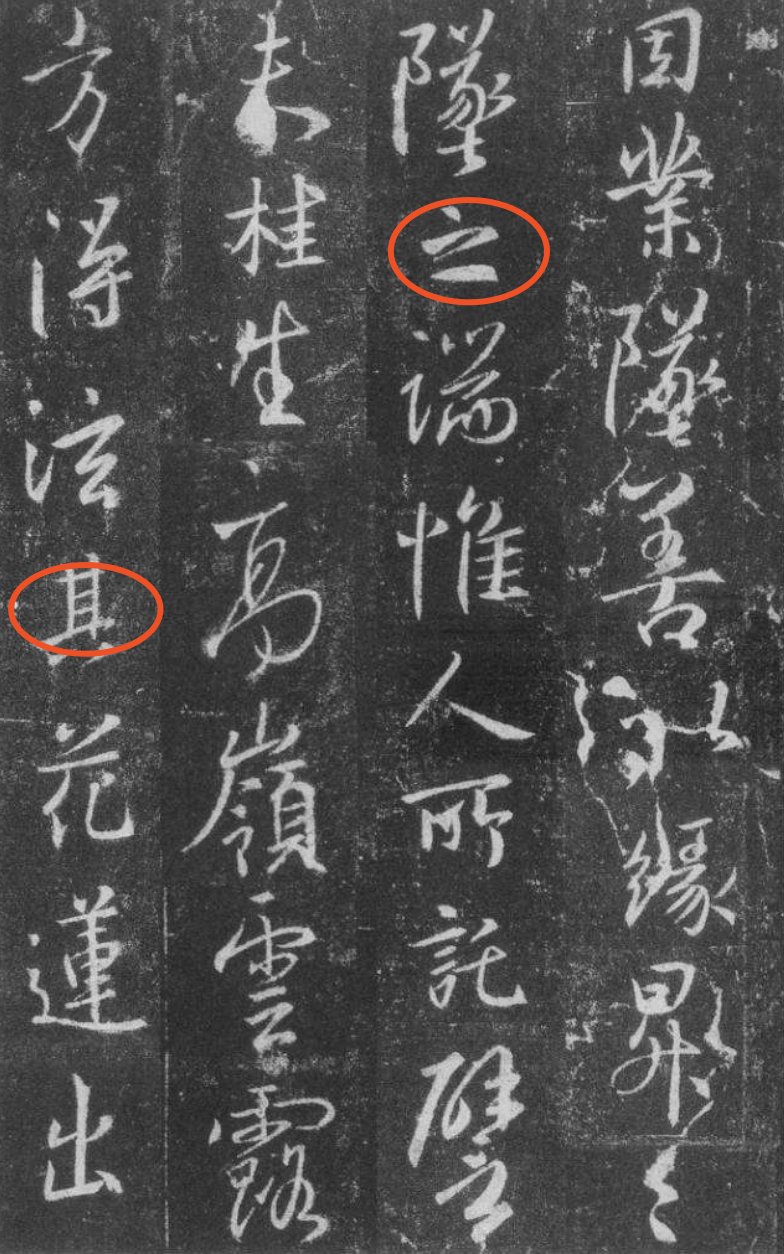
---来源:王羲之碑文
再者:要以字形的美观度来看如果定义字体的大小
以字形的美观程度来确定字体的大小和上面我提到的一样,总的来说就是字体的美观程度高的字体会写的大一些,反之从字形的美观度底的字体你就要写的小一些。一样我也找来古人的字体,从规律中确实有出现图片识别字体。
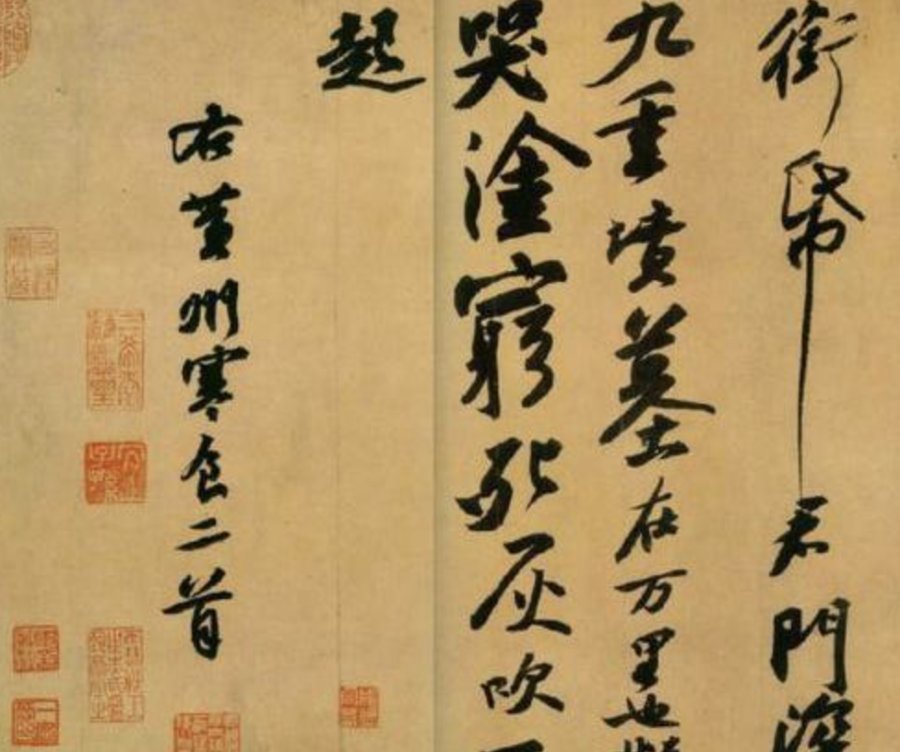
--来源:苏东坡行书
最后:字体表达情感也会以字体大小的方式来表达
古人多半出现在草书方面,表达比较强的行草书,书写的时候字都会往大了写。随着心情的起伏所以字体的大小也是表达情感而决定的。一样给你举一些我网上搜字体的例子: